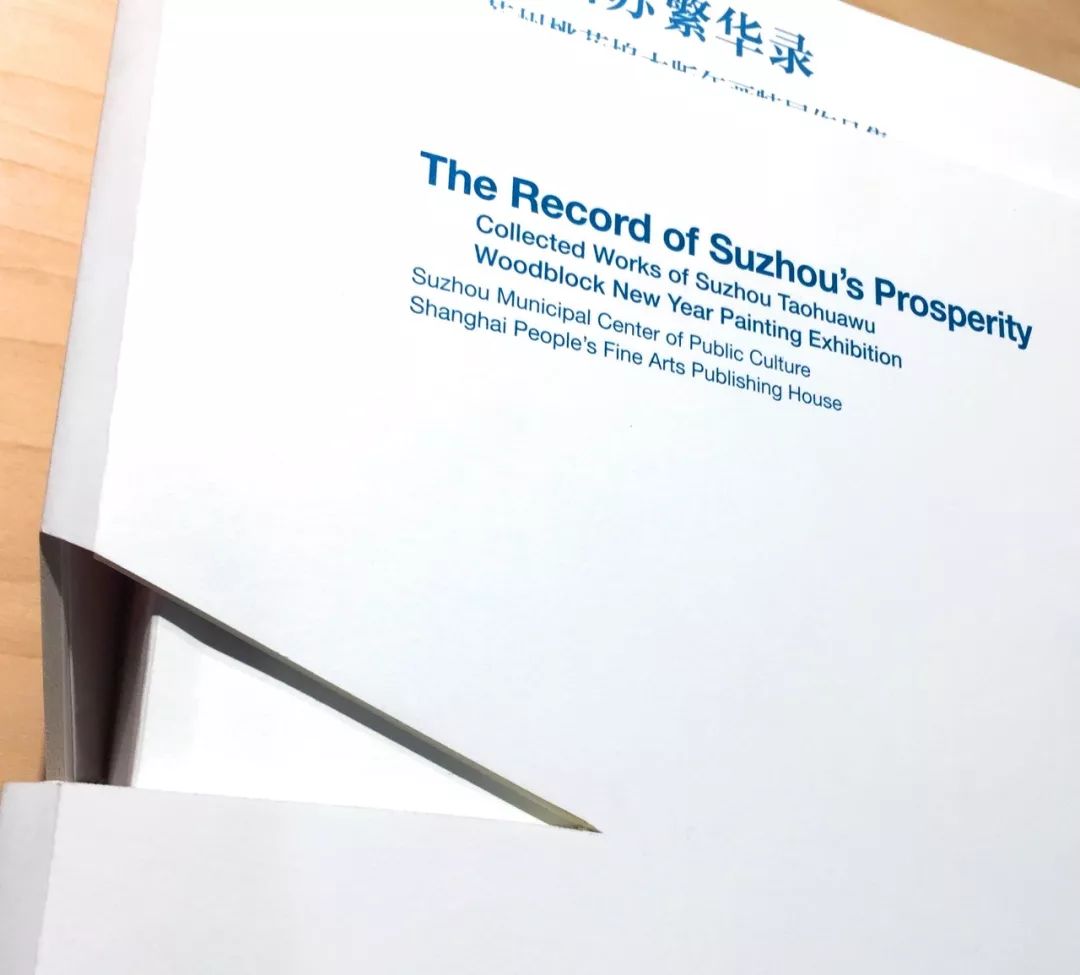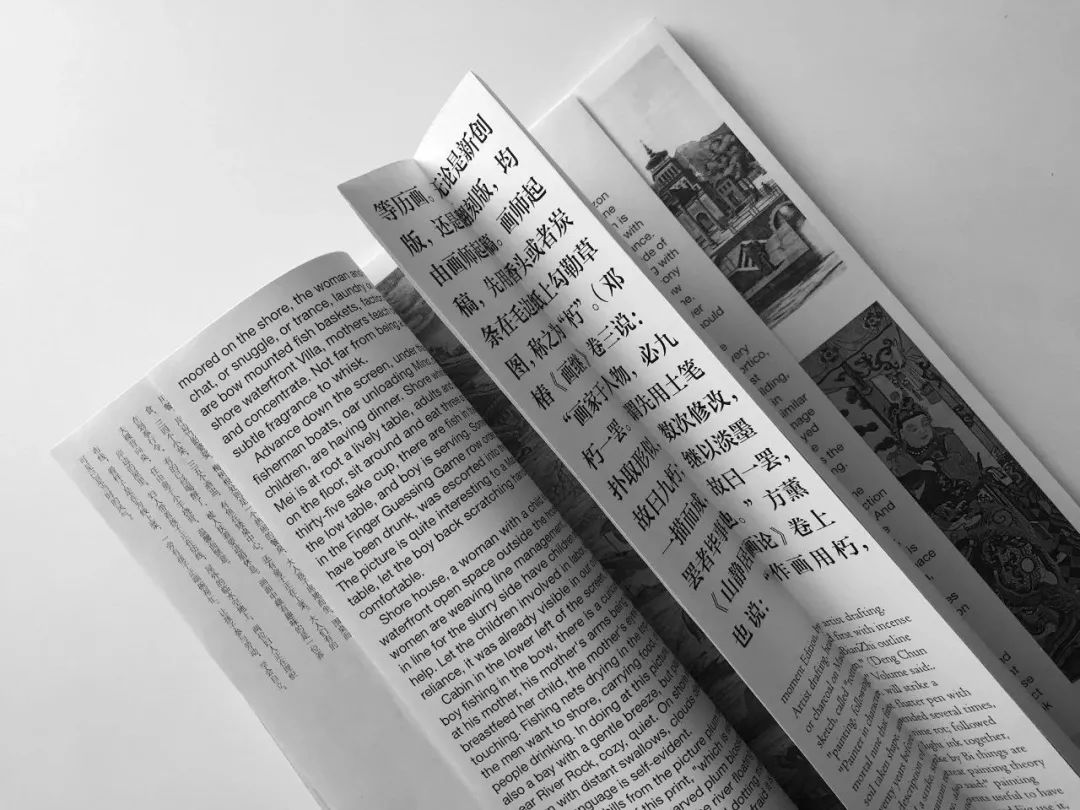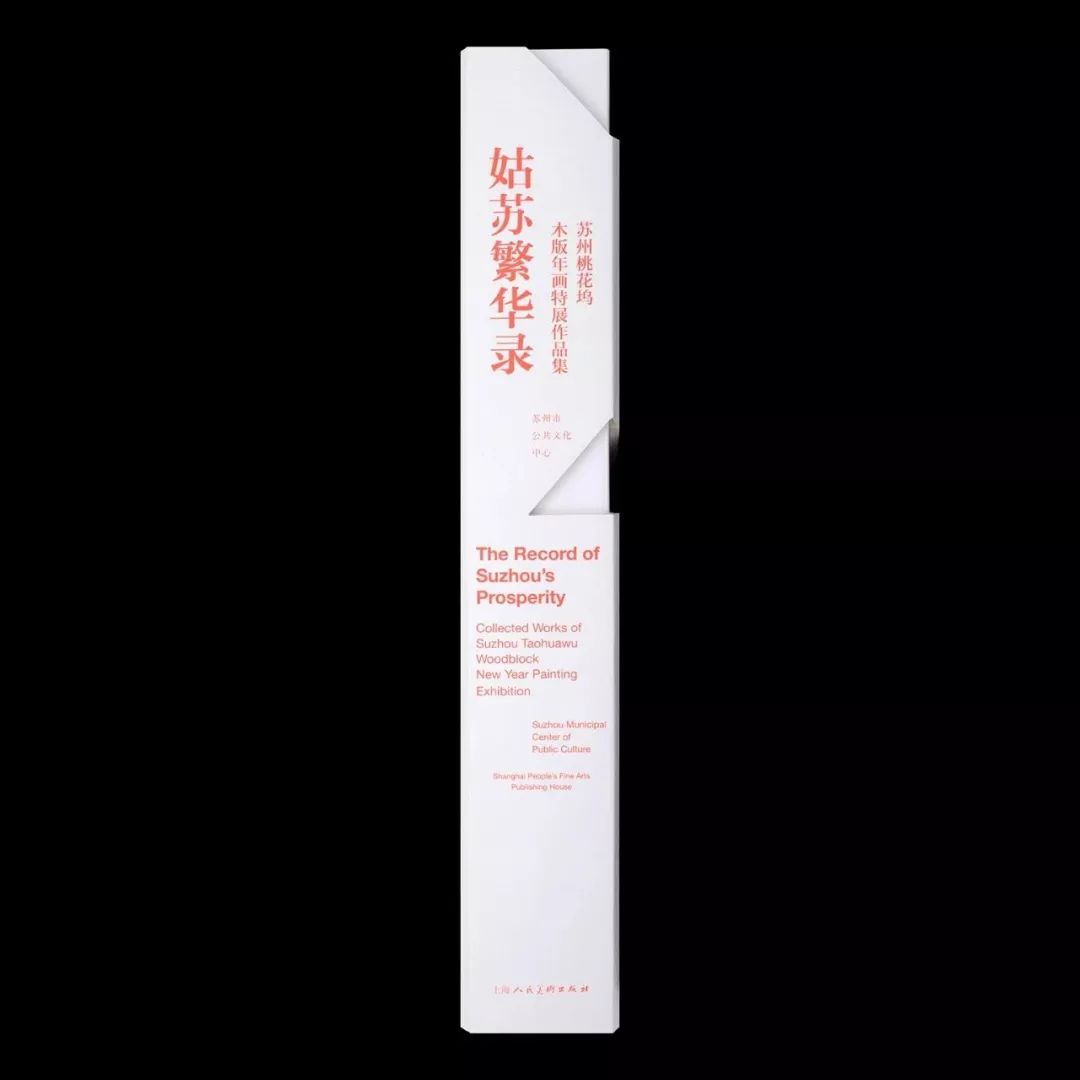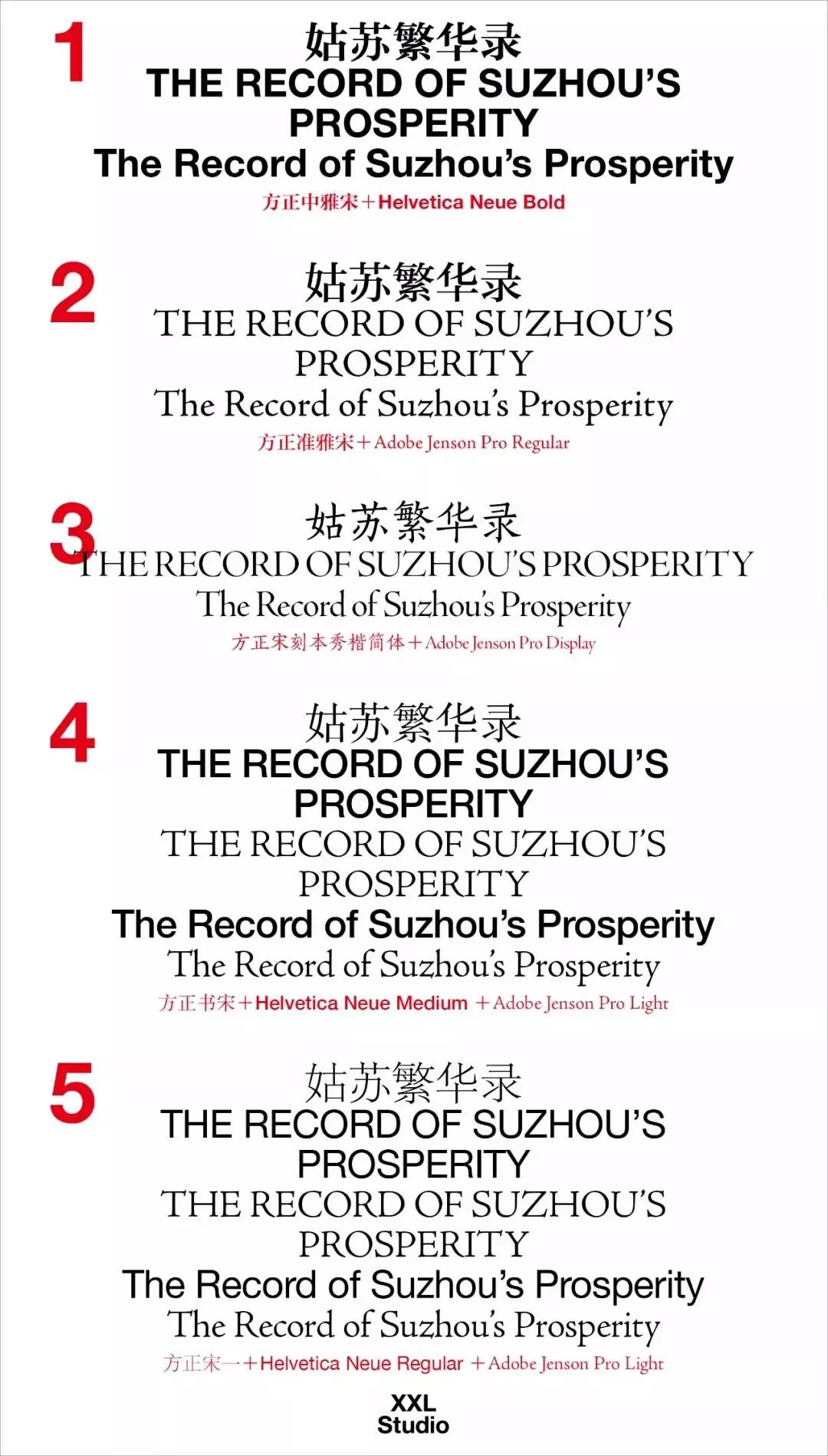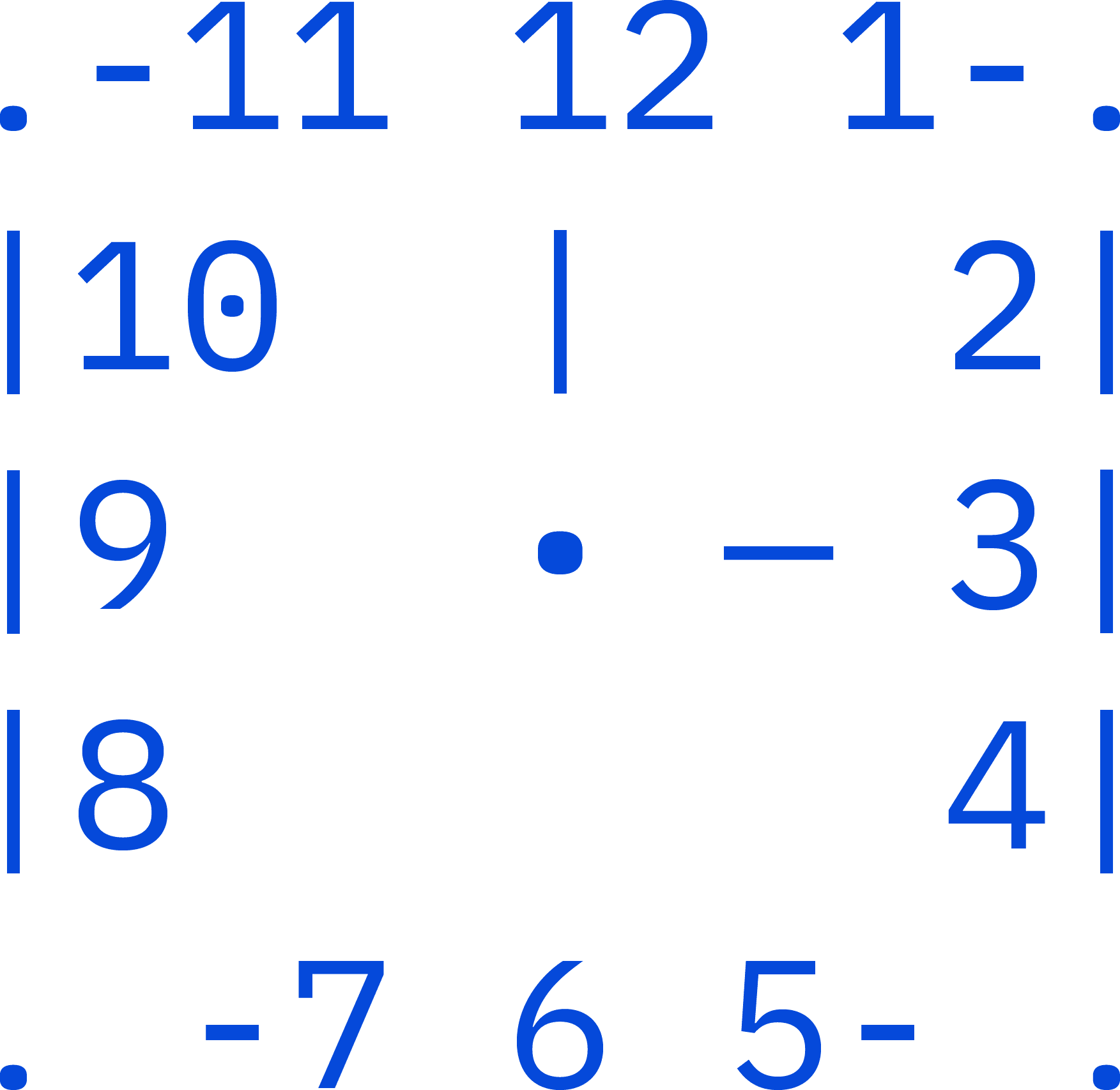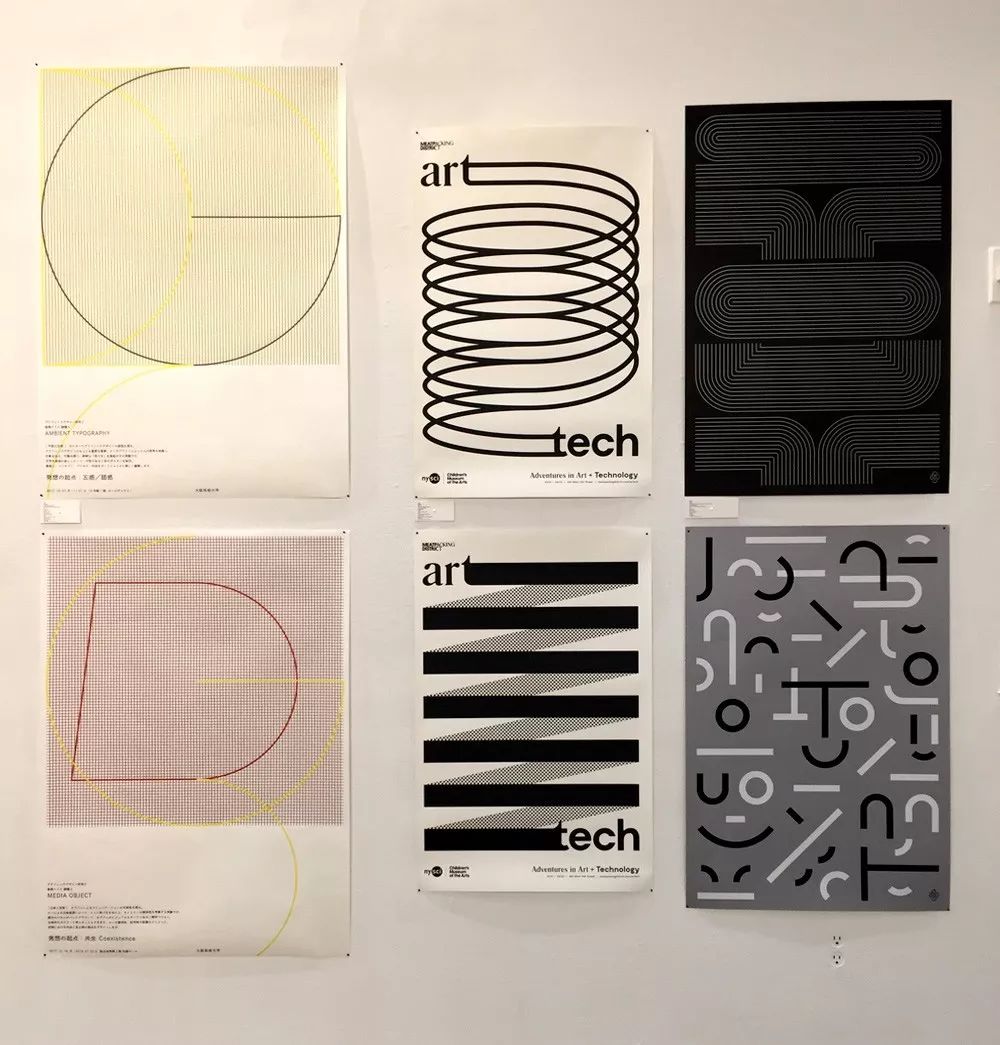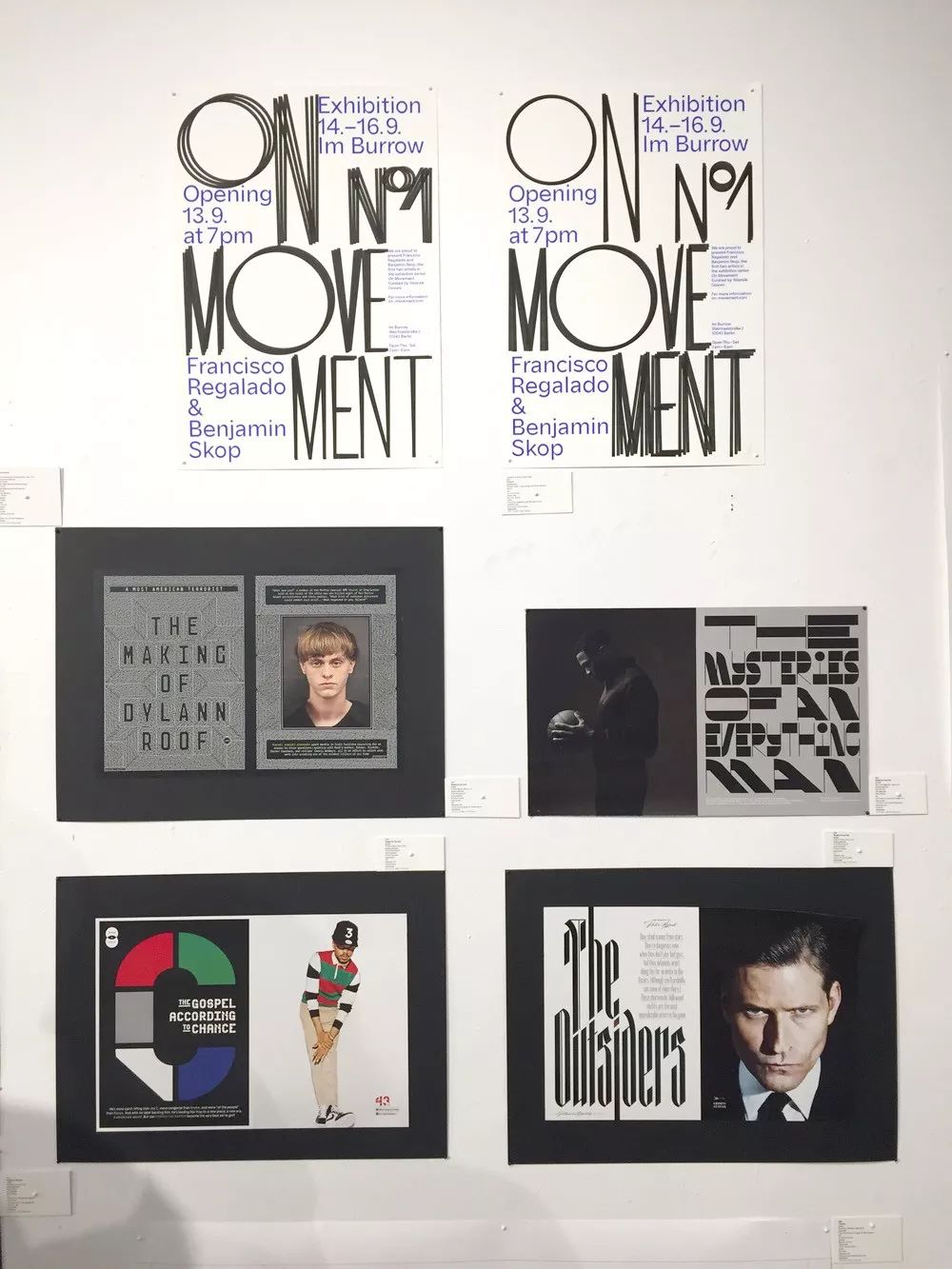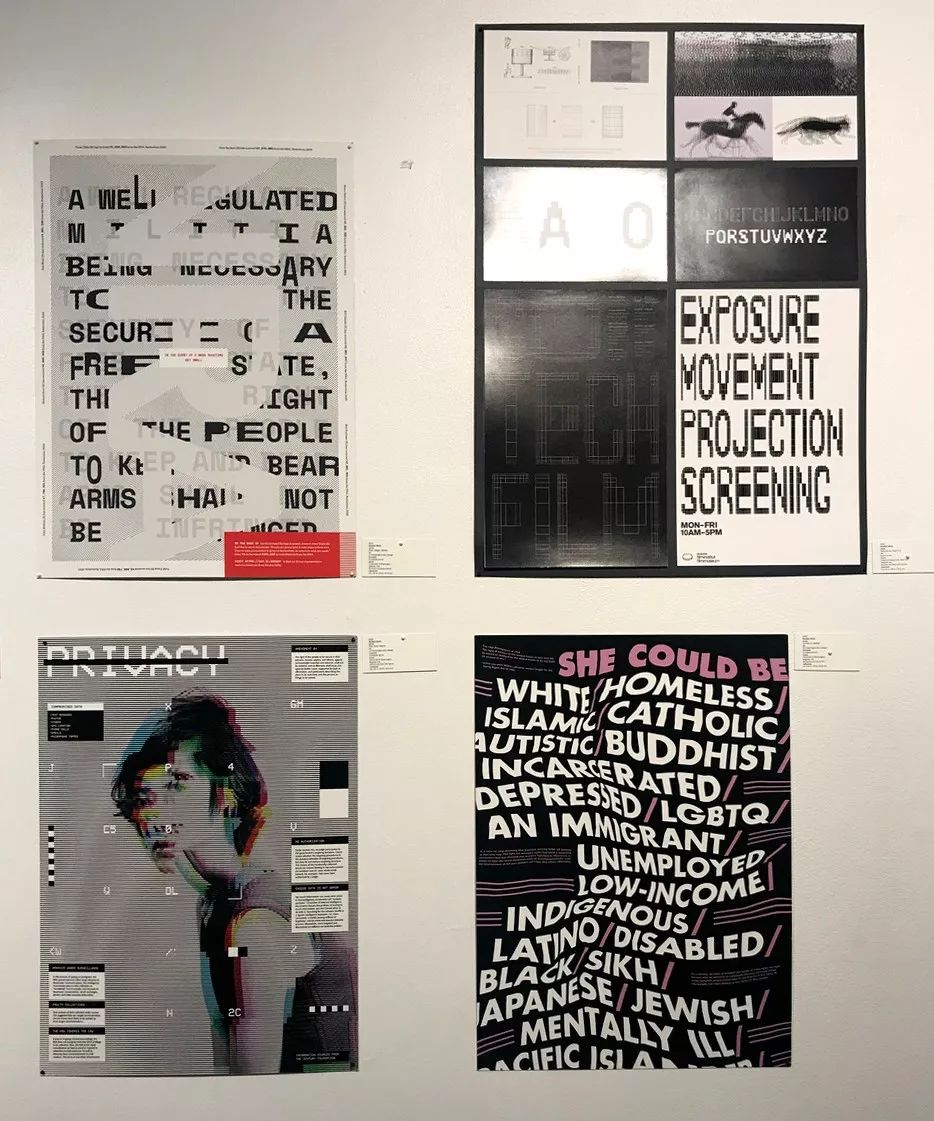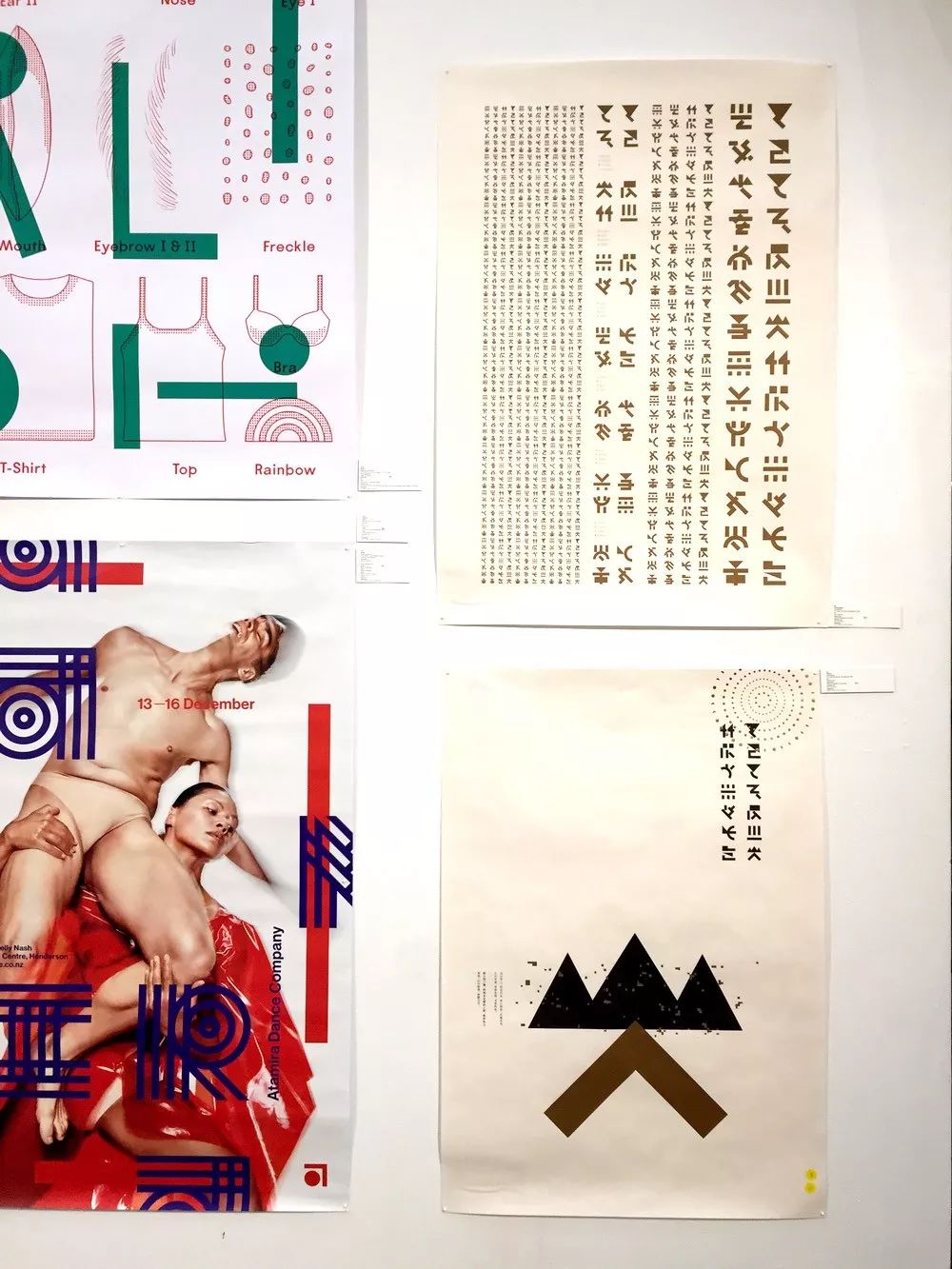
纽约TDC现场一线报道,最新获奖作品及精彩展览呈现
从2018年7月18日到8月10日,Type Directors Club和The Cooper Union正在推出世界最佳排版展览,其中包括Type Director Club第64届年度传达设计和2018年字体设计比赛的获奖作品。
今年的年度评审展览包括280多件作品,其中包括各种类别的排版,包括书籍,海报,企业品牌,徽标,网页图形,电影和电视,产品和杂志。
展出了来自许多国家的专业和学生传达设计工作,包括美国、法国、德国、日本、西班牙、荷兰、英国、中国、韩国等。
展览的一个特色是让参观者有机会近距离体验作品的实际存在,拿起书籍,检查精美的装订,触摸包装,并浏览印刷杂志。阅读这里获得最佳展示奖的书籍,以及获奖的学生可以在这里工作。
该展览在41 Cooper Square的楼下画廊展出。
TDC64 全场大奖
XXL工作室 刘晓翔
刘晓翔
《姑苏繁华录:苏州桃花坞木板年画特展作品集》便是本届备受注目的全场大奖获奖作品。
据悉,该书于2016年2月设计成形,2017年10月印装出第一批成品书。双语、木版年画和多体例复杂文本设计是这本书的几大特点,非常引人入胜。
而这本书最独特的地方可能就在于:它一直保持着最初的模样。刘晓翔表示,因受强烈的创作冲动驱使,短时间內设计方案就完全确定下来之后就没有变过:一块被木刻刀刻过的等待印刷的木版。此后,他们只是在此基础上因内容调整对页面的不断增减,再没有改动过它的初始面貌。
书籍外装设计图
因为双语的缘故,该书的设计在不同的部分使用了不同的汉字与英文字体组合。在字体选择与中西文配比上,为制造视觉冲突混合了衬线体和无衬线体。工作室称:这是考虑到Pantone荧光色的印刷,在选择大字重字体的时候会有更好的视觉效果,同时尝试大字重字体与图片形成强烈对比的页面是否还能显出“文气”。
如果说概念是一本书的灵魂,那么排版就是灵魂的又一升华。XXL Studio在排版上追求的是通过文字、图片排列,为静止的版面带来动感,形成格律之美。
TDC64 字体设计评委奖
IBM Plex字体
关于IBM Plex
字体设计:Mike Abbink(纽约); Paul van der Laan(海牙);Pieter van Rosmalen和Eindhoven(荷兰)
创意指导: Mike Abbink
字型指导: Paul van der Laan,Pieter van Rosmalen
执行团队: IBM Brand Experience&Design和Bold Monday
字体家族/系列:IBM Plex™ Sans,Mono,Condensed和Serif
IBM Plex™是IBM全球范围内全新的品牌字体,是IBM品牌与体验团队(IBM Brand Experience&Design,略称BX&D)开发的开源项目。Plex是一款多语种家族字体,旨在阐释IBM的品牌精神和历史,并展示了自本世纪初以来IBM的品牌主题——人类与机器之间的独特关系。亲切的Grotesque风格经过细致雕琢很好地平衡了它的设计,使这款中性的Plex™依然能够展现IBM的独特气质。
该家族字包括Sans,Sans Condensed,Mono和Serif,在印刷、网页和移动设备界面等方面都具有较高的易读性。Plex的三种设计既可以单独使用,也可以在一起相互匹配使用。Sans体现现代的风格,Serif可用于编辑叙事,Mono可用于显示代码片段。而斜体意外地表现出色,可为您的设计提供更多选择。
字体设计评委Verena Gerlach对IBM Plex的点评
Plex家族字是一个多功能型的家族字体,我可以想象将它应用在不同领域的场面。从代码、网页、书籍到大型展示—— 一切似乎都可以通过这款字体的不同变体实现。
纵观所有字重和风格变化,字体整体看起来非常一致。
就Sans而言,Grotesque风格的字型非常干净,所有生动而美丽的细节一目了然。字怀(Counter)的内部线条具有较大拐角(源自最初的IBM标识,但平滑了很多),这样的内部形状与非常圆的外部曲线形成了鲜明对比。
双层a和g引用了一种人文主义思想,同时又没有失去Plex Grotesque整体现代(亦兼具现代主义)的特征。它展现了理性与人性之间的平衡,而非人文主义。
一般来说,很难给予这款字一个单纯的定位,因为它结合了许多不同类型的字体的经典特征。
虽然这款字的字形比例与Helvetica(将会被Plex取代)相似,但小写字母g的小旗子状的出头却让我想起了Franklin Gothic。此外,外圆内方的设计(Oo cC Gg)让我想起了Din的字型。而且G也明显借鉴了Helvetica。
由于字干和与字干连接的部分非常开放,具有较大的白色空间,使整个Plex家族在小字号和远距离的情况下都具有较高的易读性。
我非常喜欢古怪的Plex Mono,它在技术和情感/生动感方面表现出了最佳的平衡,尤其是(真正的)斜体。
Plex Serif既有新古典主义也有点技术性,这样的结合非常漂亮!我非常喜欢它的圆滴点和圆点。这款字的衬线变体对比不强,具有现代的、相当高的x-height。它非常适合长文本的阅读排版。
TDC64 传达设计评委奖
俄罗斯革命海报
设计: Cybu Richli,瑞士卢塞恩
工作室:C2F
主要字体:定制
俄罗斯革命1917-2017海报由C2F的Cybu Richli制作。
由Serge Serov组织带领的莫斯科金蜂( The Golden Bee) 全球平面设计双年展邀请C2F的Cybu Richli为俄罗斯革命一百周年纪念活动设计一张海报。在五百张海报中,这张海报被选中参加世界巡回展览。
海报上的信息经过高度简化,只有1917和2017这两个代表年份的数字。
作品借鉴了俄罗斯的一些政治宣传海报的风格,并使用了丝网印刷技术,以朱砂红色印刷。
视觉传达设计评委 Nicholas Blechman 对作品的点评
在一个视觉爆发、到处都是弹出广告的时代,这张海报以少有的图形清晰度和力度穿透了周遭的噪音。1917-2017年的海报既复古又现代。它弥合了过去与现在之间的差距,一方面与俄罗斯解构主义设计相呼应,另一方面与现代极简主义相贴合。
要想完整地欣赏这张海报,最好是亲自去看看。经过两天辛苦劳顿的评审,在众多从电子杂志到动画等一系列作品之中,这张海报脱颖而出。获奖的一部分原因要归功于它35.2 x 50.4英寸的巨大尺寸,而丝网印刷则使它的触感更加令人印象深刻。
在这个非永久性和Instagram当道的时期,这种对手工艺和物理材料的重视很好说明了设计师的诚意。我关注Cybu Richli的工作也有一段时间了,我很欣喜地发现他和他的公司C2F都参与了这次海报相关的工作。」
TDC奖章获得者
Fiona Ross
7月18日在纽约,字体指导俱乐部(Type Directors Club,以下简称TDC)向菲奥娜·罗斯(Fiona Ross)博士颁发了最高荣誉,以表彰她五十多年来负责过世界上最具影响力的一批字体。
据TDC执行董事卡洛尔·瓦勒(Carol Wahler)说「无论是作为曾经Linotype的员工,还是作为现在一位受人尊敬的教授,菲奥娜都是一位睿智而高尚的女性。她大大提升了人们对非拉丁文字体的理解和欣赏能力。TDC董事会一致决定将TDC奖章授予菲奥娜,以表彰她在字体社区中的影响力和成就。」
菲奥娜·罗斯于1978年开始在Linotype工作,当她作为第一位女性经理担任非拉丁字体部门的领导时,该部门诞生了很多世界上使用广泛的设计。目前,她与Tiro Typeworks合作开发新字体,并为其他字体设计公司提供咨询服务。在雷丁大学,她教授非拉丁字体设计,并为文字排版和平面交互项目的研究生提供建议。她的著作《印刷孟加拉文及其演变》,成为了这门全世界超过2.5亿人使用的语言的文字排版的主要参考资源之一。
Fiona Ross设计的字体作品,在世界各地的应用
现在担任Adobe Type高级经理的丹·拉蒂根(Dan Rhatigan)也是罗斯博士的学生,而他评论道「菲奥娜最不平凡的品质是她对自己影响力的评价所展现的谦逊。即便她通过自己以及学生几十年来的工作和研究提高了全球文字排版的标准,她依然坚持自己不是专家,只是专注于文字行业而已。」
菲奥娜·罗斯和丹·拉蒂根
按照传统,TDC奖章会授予对文字排版领域做出重大贡献的个人。
Fiona Ross是TDC奖章的第31位获奖者,该奖章于1967年首次由TDC授予赫尔曼·扎普夫(Hermann Zapf),以表彰他对排版的贡献。之后的获得者包括保罗·兰德(Paul Rand),马修·卡特(Matthew Carter),埃里克·斯皮克曼(Erik Spiekermann),阿德里安·弗鲁蒂格(Adrian Frutiger),格里特·诺泽尔(Gerrit Noordzij),博兰·雪(Paula Scher),路易斯·菲利(Louise Fili),埃德·本格伊特(Ed Benguiat)和杰拉德·昂格尔(Gerard Unger)。
纽约字体指导俱乐部(Type Directors Club)
聚集并支持国际范围内文字设计领域的领袖设计师们已经超过70年的历史。这其中最主要的方式就是通过一年一度的TDC大赛,分别在“传达设计”和“字型设计”两个版块挑选出当年来自包括美国在内全世界各地的设计工作室和独立设计师们最出色的作品。
传达设计比赛:今年,Chris Sergio 和 Catherine Casalino 作为两位联合评委会主席和俱乐部委员会一起挑选了7位来自不同设计领域的专业评委,包括:Nicholas Blechman,Mike Essl,Bryony Gomez-Paolacio,Nathasha Jen,Jon Key,Gemma O’Brien 和 Susan Sellers。评委会从来自55个国家的2000多名参赛作品中选出265名获奖者。
字型设计比赛:Elizabeth Carey Smith 作为今年的评委会主席和其他四位评委一起主持赛事的评选,分别是 Sahar Afshar,Verena Gerlach,YuJune Park 和 Dyana Weissman。评委会从39个国家的225多个参赛作品中选出了18名字体设计获奖者。
展览作品现场分享